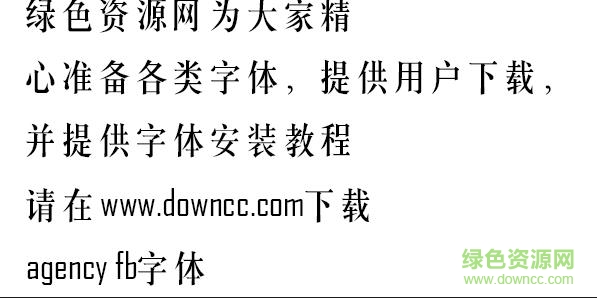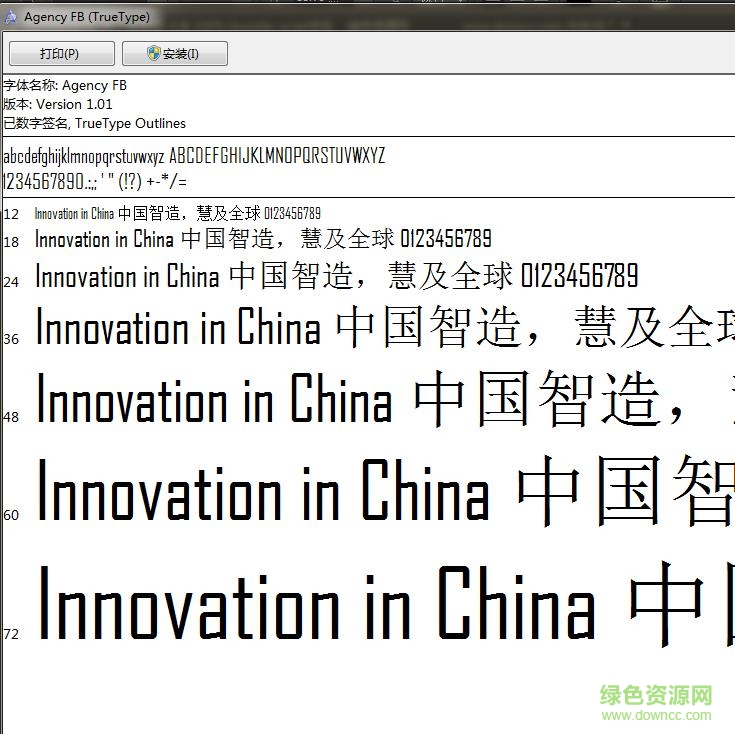
agency fb英文字體ttf中每一個字母如果是封閉的樣式將看到一個個四方形的圈,讓你感受到獨特的視覺享受,它的風格十分有趣,很適合應用到孩子所喜愛的場所或者書籍中,快來綠色資源網(wǎng)下載吧!
agency fb字體將帶給你獨特的英文字體樣式體驗,是一款能夠讓你立刻愛上它的優(yōu)質字體,運用范圍十分廣泛,受到萬千用戶喜愛!